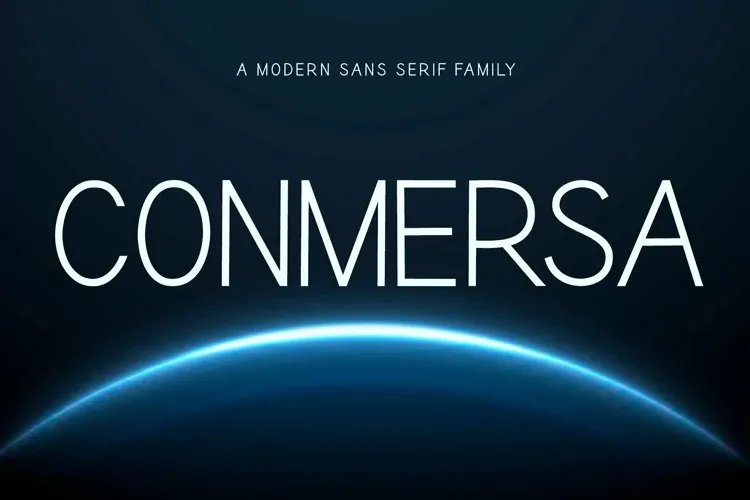
Esta família de fontes é composta por quatro estilos que se complementam perfeitamente. Ela foi criada pelo designer AEN Creative Studio e se destaca pela sua simplicidade e elegância, sendo um tipo sans-serif minimalista e aconchegante. Ideal para quem busca uma fonte que possa ser facilmente combinada a um número imensurável de projetos, ela adicionará profundamente à criatividade dos seus ideais visuais, ressaltando-os em cada conceito. Com seu design limpo e eficiente, esta font não apenas se encaixa perfeitamente com diversos estilos de criação como também oferece uma versatilidade que pode ser usada para dar um toque diferenciado a qualquer projeto gráfico. Seja para artigos de blog ou portfolios de designers, esta família de fonts sem serif é uma escolha inteligente para aqueles buscando algo moderno e fácil de combinar.